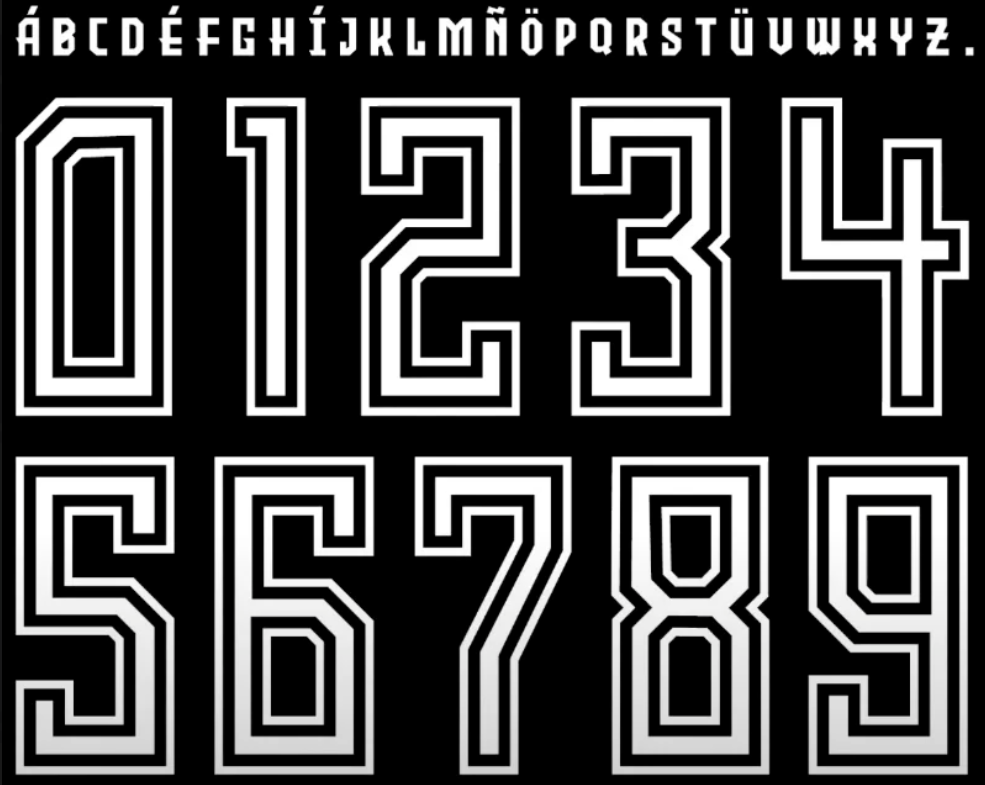
A paixão da Massa Atleticana é vista em cada detalhe. Na temporada 2024-2025, o Manto Alvinegro, assinado pela Adidas, ganha contornos únicos, e a tipografia oficial é uma peça-chave dessa identidade.
Se você é designer, trabalha com personalização (seja em mockups ou silk screen) ou é um torcedor que busca replicar o visual exato dos uniformes do Atlético Mineiro, você chegou ao lugar certo. Disponibilizamos a fonte exata usada nos nomes e números dos jogadores para a temporada 2024-2025.
O Estilo Visual: A Assinatura Adidas
A tipografia desenvolvida pela Adidas para o Atlético Mineiro na temporada 2024-2025 foca em legibilidade e modernidade.
É uma fonte display (feita para ser vista), com traços robustos e cantos levemente chanfrados que transmitem uma sensação de energia e velocidade. Diferente de fontes mais arredondadas, este design é mais angular e agressivo, alinhando-se perfeitamente ao espírito competitivo do Galo.
Você verá essa tipografia marcante sendo usada por craques como Hulk e Paulinho, estampando os nomes e números tanto no uniforme principal (listrado em preto e branco) quanto nos uniformes de visitante e alternativos da temporada.